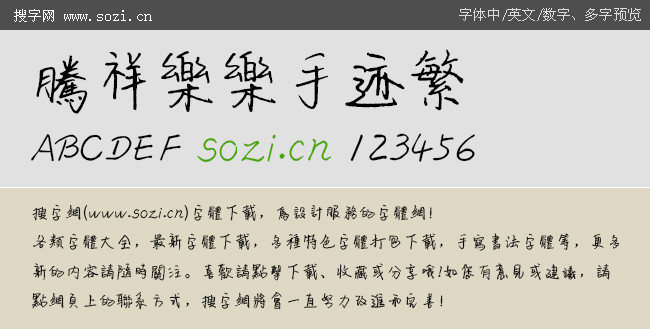
騰祥樂樂手跡繁
搜字網(wǎng)提供一款騰祥樂樂手跡繁中文藝術(shù)字體下載,騰祥樂樂手跡繁是一款很漂亮的手寫字體,書寫風(fēng)格自然流暢,獨(dú)具風(fēng)格,稚拙中透顯出活潑靈動的氣息;無雕琢,無拘束質(zhì)樸的視覺效果,用于正文更體現(xiàn)出手寫自然之感。字體可以廣泛應(yīng)用于印刷出版、包裝設(shè)計(jì)、廣告設(shè)計(jì)、網(wǎng)頁設(shè)計(jì)等領(lǐng)域。